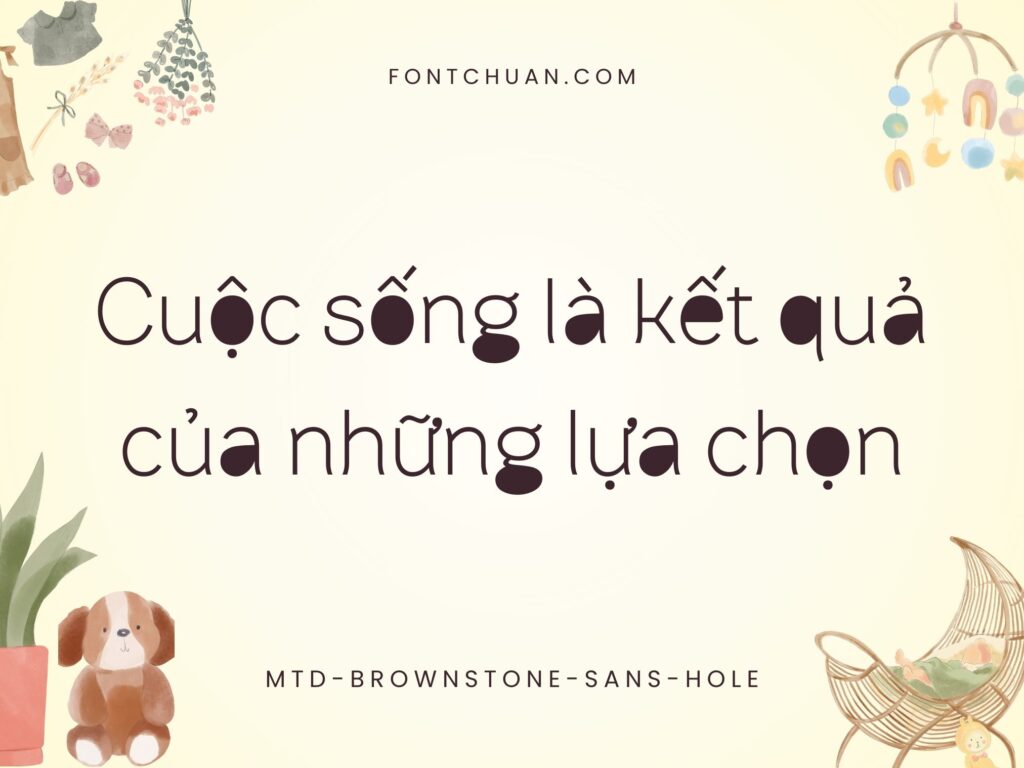
Font MTD Brownstone Sans Hole Việt Hóa
Tác giả Font: Hart Foundry™
Font MTD Brownstone Sans Hole là một kiểu chữ sans-serif trang trí độc đáo, được thiết kế bởi Alejandro Paul và đã được Việt hóa bởi Mộc Hạ. Font này hỗ trợ đầy đủ tiếng Việt cùng hơn 90 ngôn ngữ khác, mở rộng khả năng ứng dụng trong các thiết kế đa ngôn ngữ. Đây là một trong những phông chữ được cộng đồng thiết kế đánh giá cao và sử dụng trong nhiều dự án sáng tạo, đáp ứng nhu cầu đa dạng của người dùng.
MTD Brownstone Sans Hole nổi bật với các đường nét mềm mại và phong cách trang trí đặc sắc, mang đến cảm giác hiện đại và nghệ thuật. Font rất phù hợp cho các thiết kế logo, tiêu đề, bao bì sản phẩm, thiệp mời và các ấn phẩm đòi hỏi sự tinh tế và độc đáo. Các ngành nghề phù hợp bao gồm quảng cáo, giáo dục, công nghệ, thiệp cưới và ảnh cưới. Font này cũng lý tưởng cho các sự kiện như Tết, Giáng sinh, Valentine và các lễ hội khác.